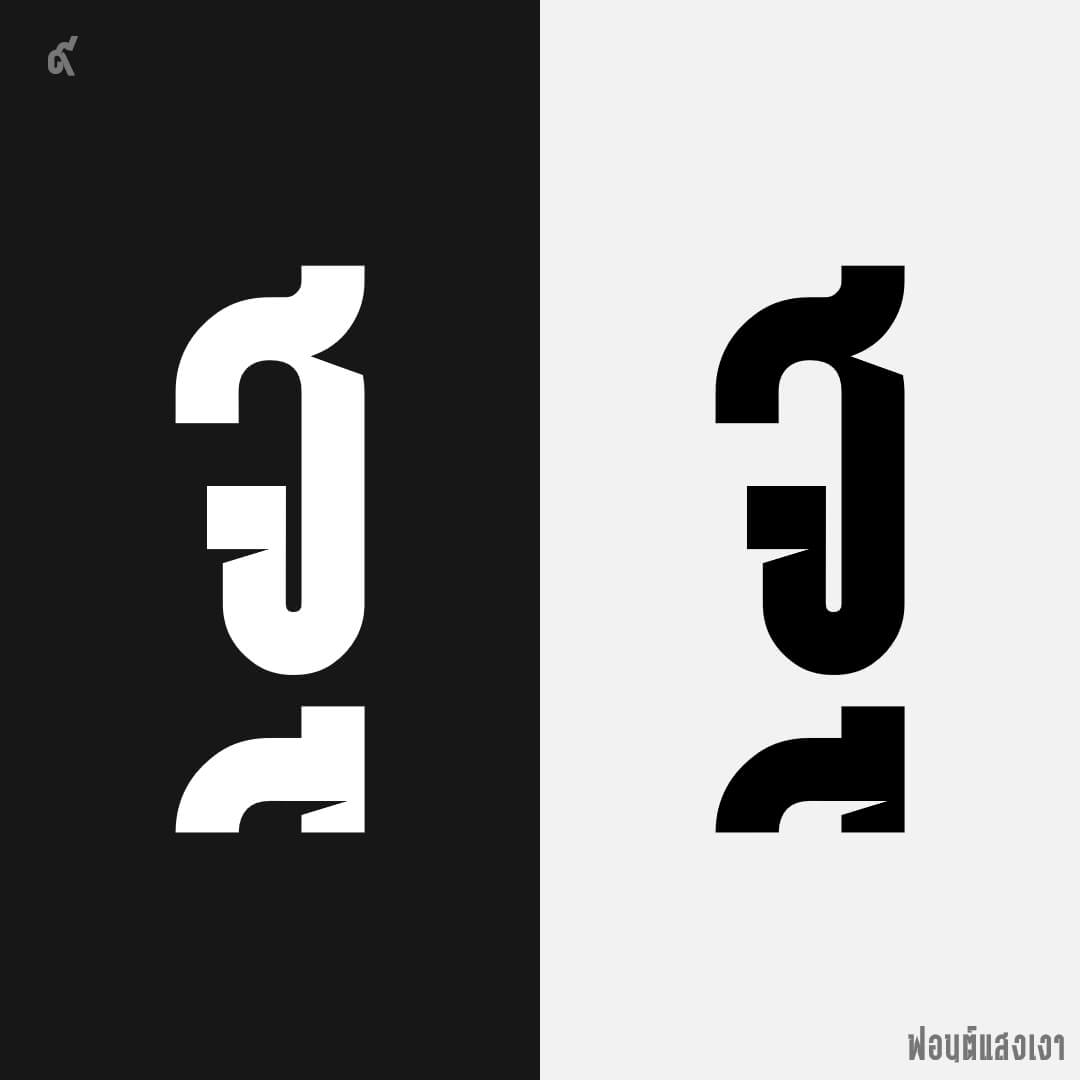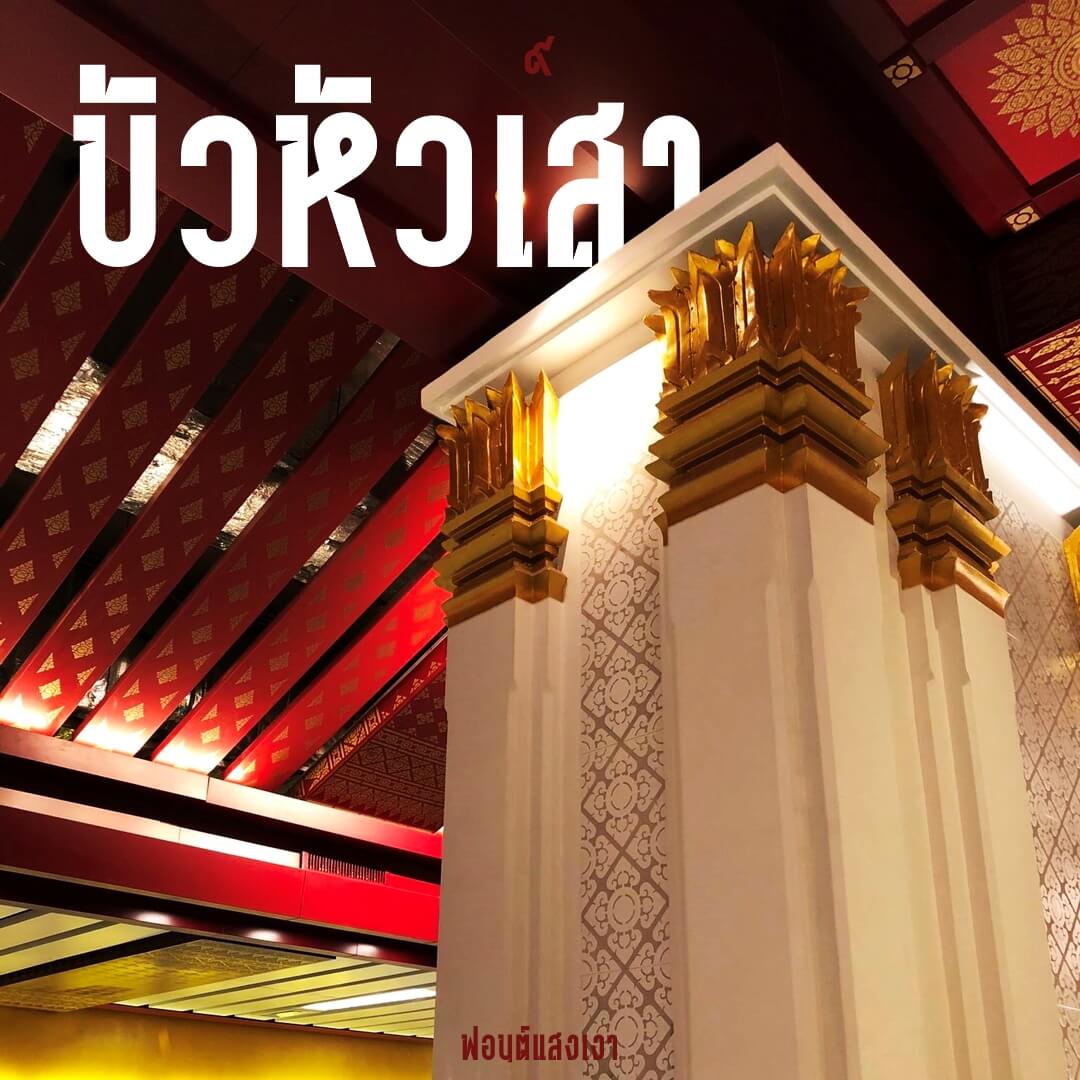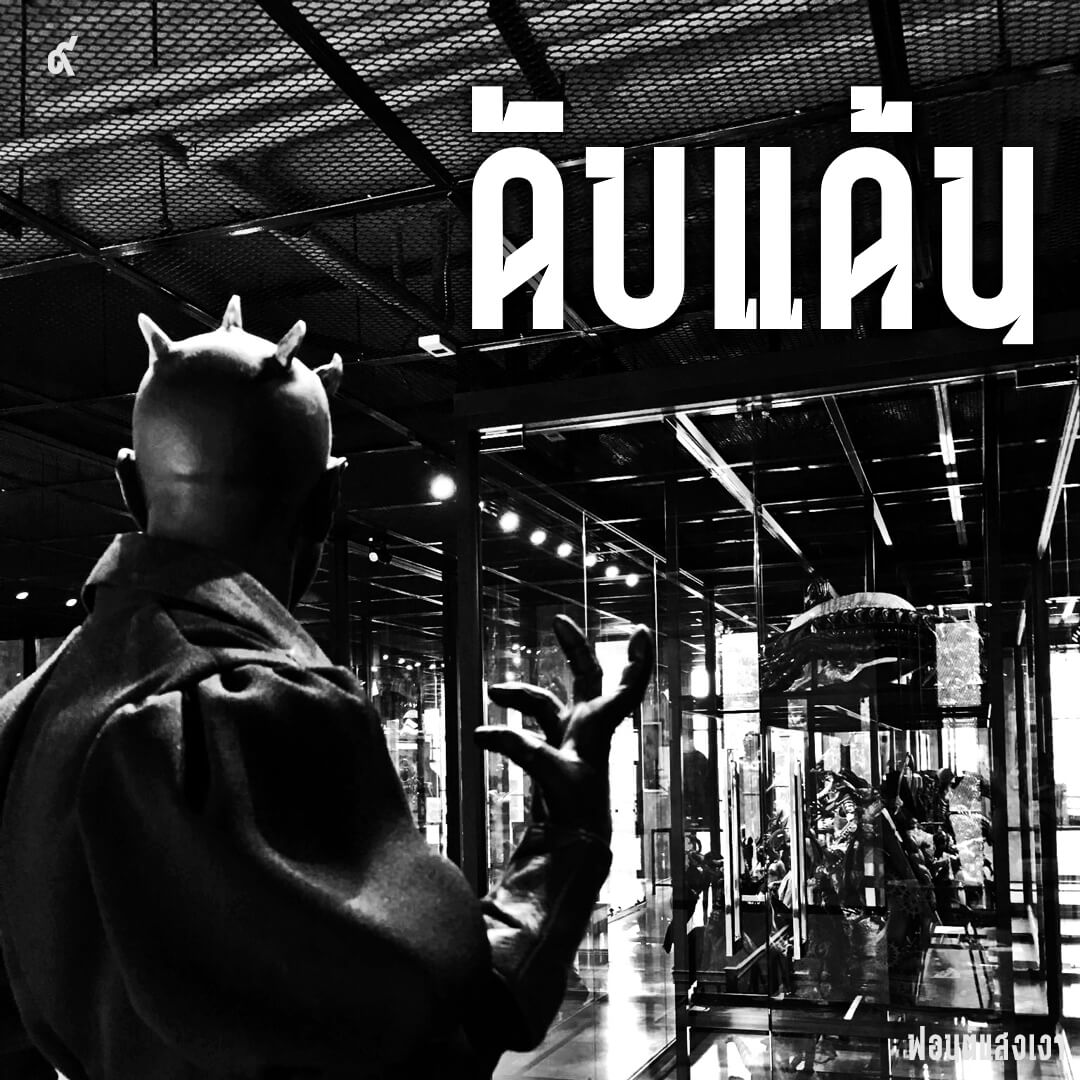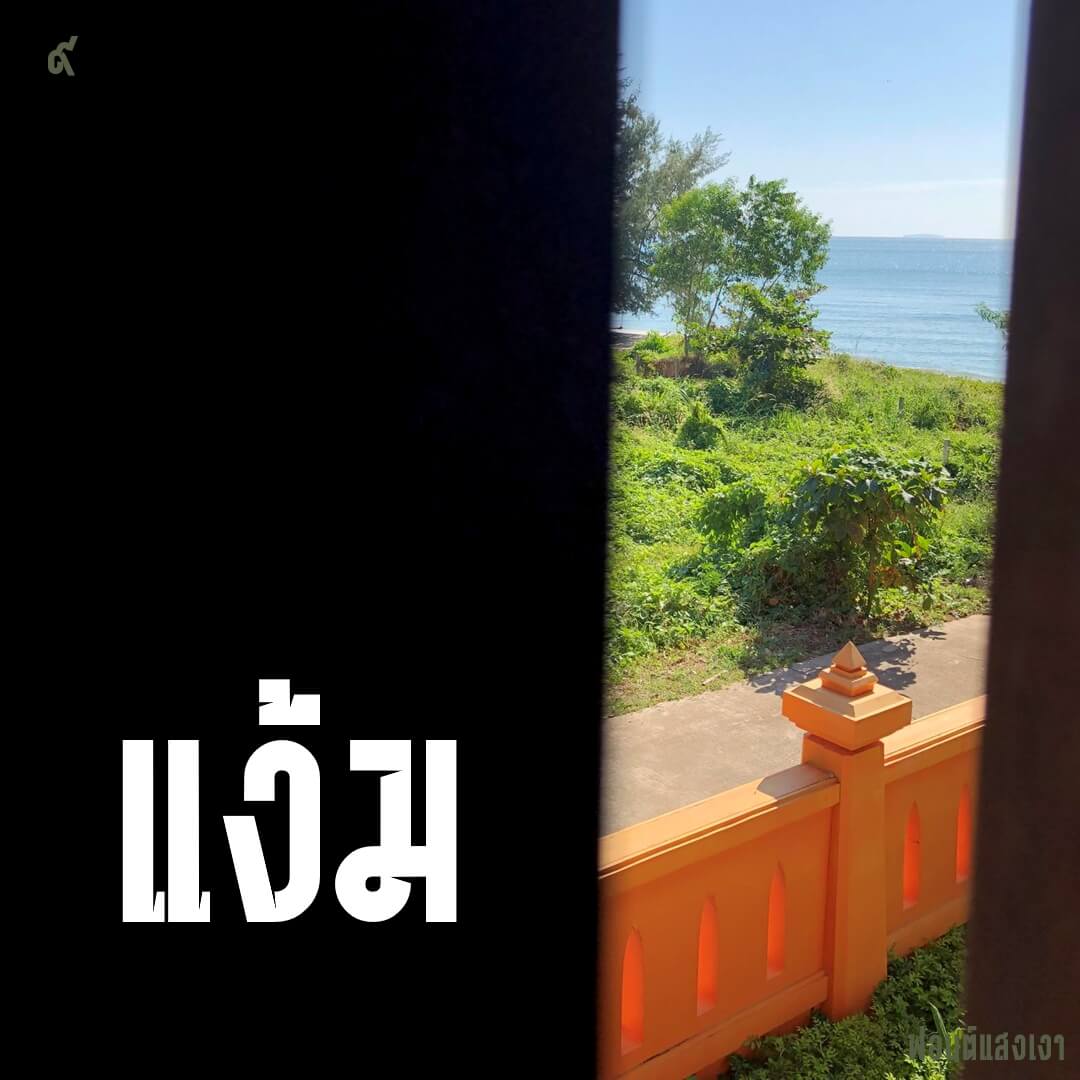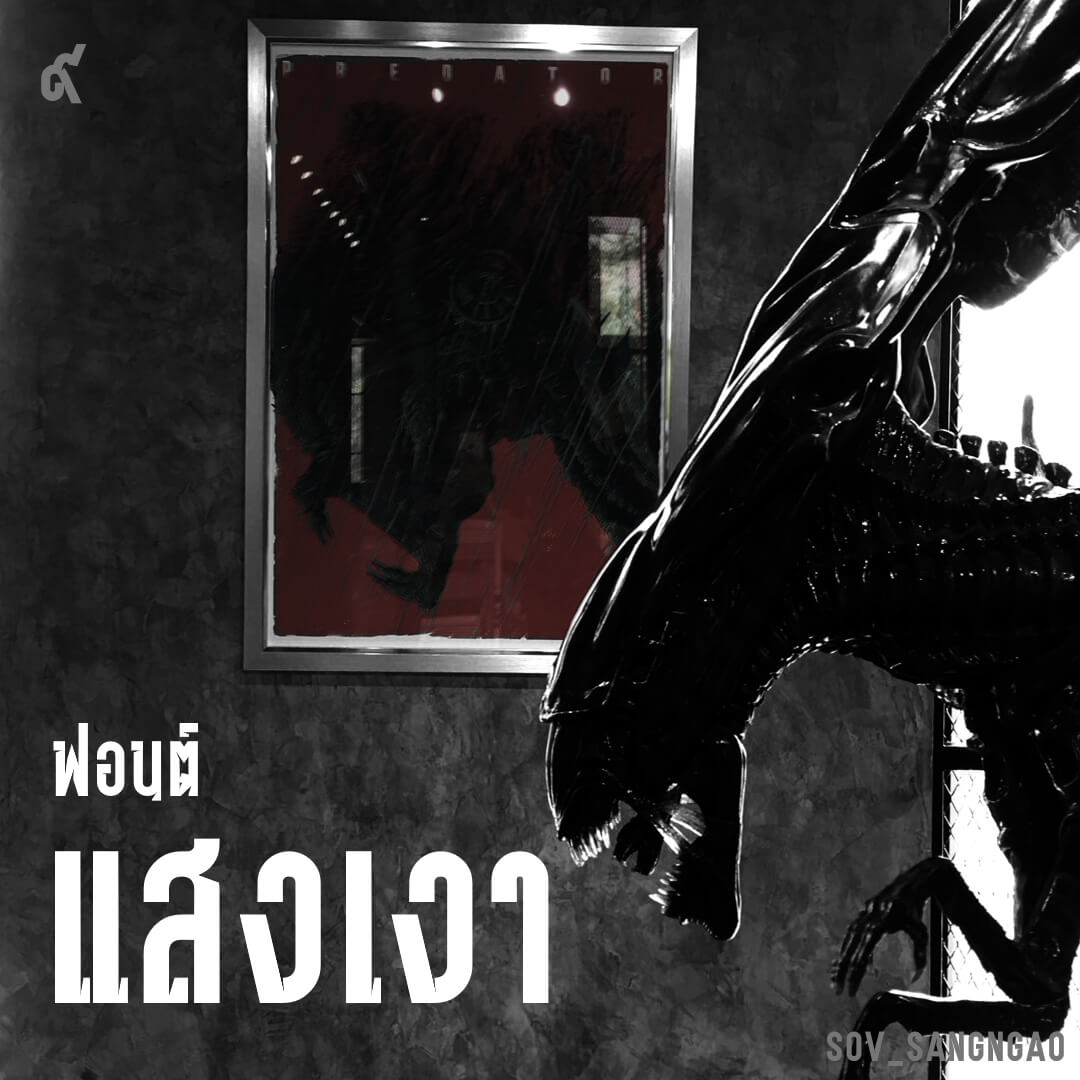
แสงเงา (SOV_SangNgao)
ไปเจอฟอนต์ฝรั่งที่มีร่องดักหมึกลึกสะดุดตา… น่าสนใจ เลยใช้เป็นโจทย์ไว้ออกแบบ
ตั้งเป็นโจทย์ไว้ 2 ข้อ
1. ร่องดักหมึก (ink trap) ต้องเป็นเงาที่เกิดจากแสงด้านซ้ายบน
2. พยัญชนะต้องมี ความหนาเส้นเท่ากันหมด (monoline) ห้ามใช้วิธี illusion ขนาดเส้น โดยต้องไปปรับสมดุลของ ink trap กับ monoline ให้ได้
ผลที่ได้… ถ้าตัวอักษรเข้มบนพื้นจาง ก็จะได้อักษรแปลกๆ  แต่ถ้าวางตัวอักษรสีอ่อนบนพื้นเข้ม จะเห็นเป็นเงา แทนร่องดักหมึก